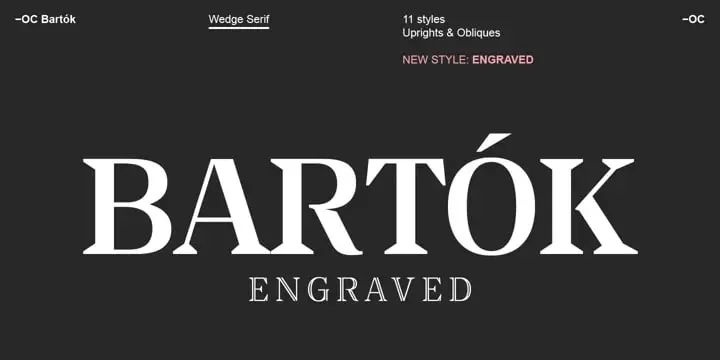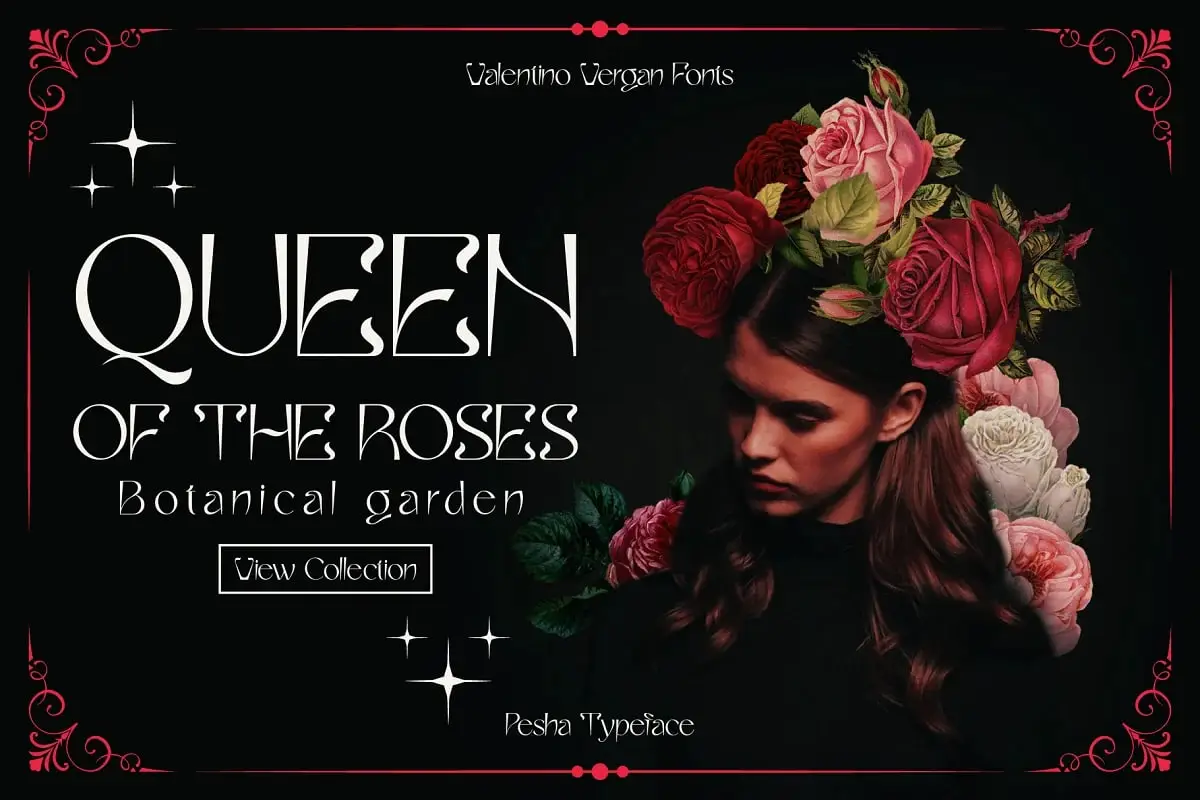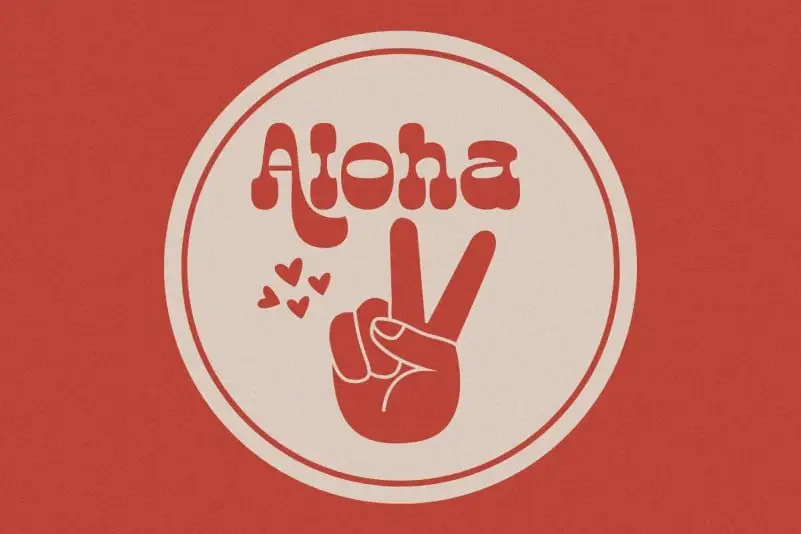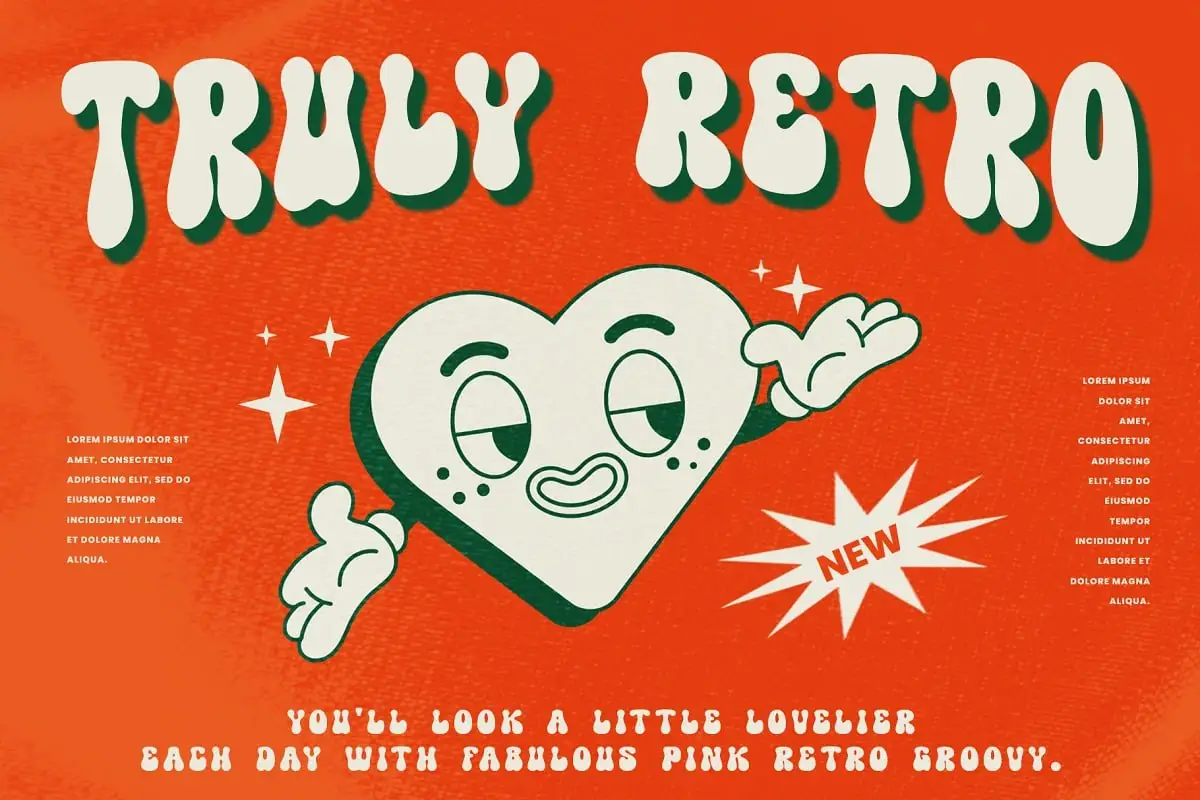
20个来自BrushesPack合集第110部分必备字体与设计素材 🎨✨
Typealiens 2021-Quint Cverto
用这款数字设计素材释放超凡脱俗的魅力。它富含高清元素,完美适配科幻海报或需要宇宙风格的品牌设计!🌌✨
Stencilul By Storm Type
用这款模板字体获取原始的街头艺术风格。非常适合海报、专辑封面以及任何需要工业感、大胆态度的设计!🎤🔨
Steppe 1 0 By Igor Stepanchenko
一款多功能、高品质的设计素材,为任何项目带来清新、现代的感觉。无论是个人还是商业用途——您的工作流程会爱上它!🌿
超级复古-时髦复古字体
Super Retro-Groovy Retro Typeface
太酷了,宝贝!这款字体融合了纯粹的70年代迪斯科能量,拥有俏皮的曲线和大胆的字符,完美适用于派对传单、复古品牌推广和趣味社交媒体。🕺💃
Shin Typeface By Hvnter
干净、优雅,且极具可读性。这款现代字体是标志、标题和正文的绝佳选择——并提供多种字重!📐✨
Retro Volt 字体 by Nirmana Visual
Retro Volt Font By Nirmana Visual
用复古电流点亮你的设计!这款字体融合了复古美学与现代实用性——非常适合标志、品牌和引人注目的标题。⚡🎸
桑加尔斯重金属字体 — Julpik 设计
Sangars Heavy Metal Font By Julpik
把音量调大!这款粗犷、有质感的字体充满态度——非常适合乐队周边、游戏图形,或任何需要呐喊的项目。🤘🔥
Pangram Foundry-Neue Machina 字体(个人使用免费)
Pangram Foundry-Neue Machina Typeface (Free For Personal Use)
免费获取这款顶级的几何字体!线条干净利落,多种字重可选,用于个人项目和设计稿简直太划算了。💸🎁
Pesha-Art Nouveau Typeface By Valentino Vergan
优雅的化身!这款线条流畅的华丽字体,是婚礼请柬、奢侈品牌和复古风格艺术的梦想之选。🌸🖋️
Otherwherecollective Oc Bartok 字体家族
Otherwherecollective Oc Bartok 字体系列
一个完整的字体系列,尽显全能。现代、清爽,完美适用于品牌设计或UI界面——多种样式供您尽情发挥!🧩
Northwild 字体
质朴魅力与现代设计的完美结合!这款字体非常适合户外品牌、温馨咖啡馆,或任何需要自然、大地风格的项目。🌲🏔️
Parodisme 字体
俏皮、艺术且独树一帜。这款字体为标志设计、产品包装或儿童书籍封面增添了奇思妙想的魅力。让你的创意尽情绽放吧!🎭🌈
Platia
一个现代化、多用途的素材,既适用于数字项目,也适用于印刷项目,效果出色。其简洁的美学风格使其成为打造精致品牌的明智之选。🖼️✨
Mess In Keytic
为你的视觉叙事增添一种混乱而富有创意的独特风格。这款可自定义的素材非常适合喜欢前卫、独特图形的营销人员和设计师。 🖤🌀
美杜莎字体(版权归 Benjamin Vernon 所有)
Medusa Typeface (C) Benjamin Vernon
迷人而现代,这款字体将经典优雅与当代锋芒巧妙融合。适合高端品牌和编辑排版,令人惊艳。🐍✨
Nima-Modern 展示字体
Nima-Modern Display Typeface
引人注目且优雅,这款展示字体专为需要吸引眼球的标题而设计。非常适合现代品牌推广和宣传材料。💎
Modernita 0 1 字体 西里尔文 由 Emmeran Richard 设计
Modernita 0 1 Font Cyrillic By Emmeran Richard
一款简洁现代且全面支持西里尔字母的字体!非常适合多语言项目或需要时尚国际风范的设计。🌍📝
Neima
Neima 品质卓越且高度可定制,是品牌与网页设计的理想之选。其对细节的精益求精能瞬间提升任何项目的档次。🌟
多类型行布局
Multitype Rows
一套专为 UI/UX 和网页设计师准备的精彩可定制行布局合集。助您快速构建美观且响应式的布局!🧱💻
Mbf 太空栖息地字体(Bramaji Dipa Manggala 设计)
Mbf Space Habitat Font By Bramaji Dipa Manggala
搭乘这款几何科幻字体,冲向未来!完美适用于科技品牌、游戏设计或任何需要未来感的项目。🚀👾